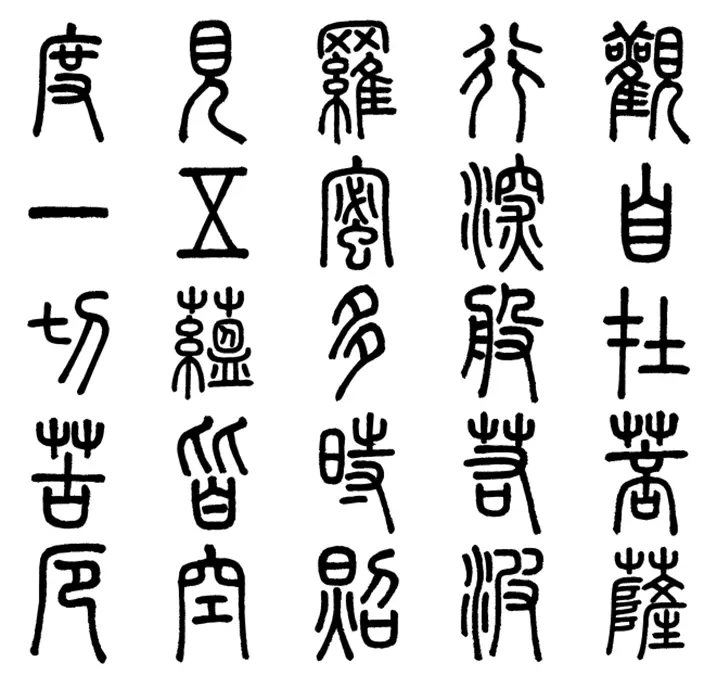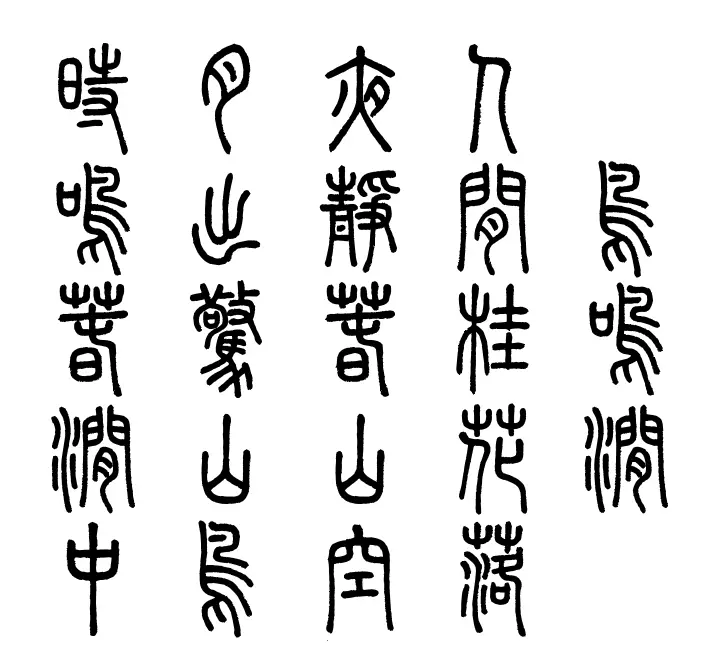
小篆是漢字的優秀字形,是人類文明的瑰寶,二千年來,深受廣大人民的喜愛。
小篆字形以《說文解字》為依據,《說文解字》雖然有一些板本的差異,但在文字學家的努力之下,絕大部分已取得一定的共識,問題不大。問題最大的是《說文解字》未收字,或《說文解字》之後產生的漢字。這些字沒有篆體,廣大的小篆喜愛者深感苦惱。歷代書法家也個別為一些字轉寫為篆體,但是沒有全面系統化的進行,也未能進入現代的電腦字體,所以當代的使用者無法享用到這些成果。也有電腦字體公司完成了全套的篆字字體,但是並未請教文字學家,所以成品難以過關,如「有」字寫成「」、「為」字寫成「」、「丟」字寫成「」等,都是讓人無法理解的形體。
王心怡女士學習小篆逾三十年,在臺師大、北師大學習文字學,又花了很大功夫編制《商周圖形文字編》,認認真真的把文字學專業學習通透。她有特殊的感受力,感受到上天要她完成篆字的書寫。而一向對電腦中文關心備至的謝清俊教授也提議要開發一套適合各界使用而又合於文字學專業要求的全篆字,在各種因緣具足的條件下,心怡欣然接受了這個任務。在謝教授的領導下,莊德明先生和我義無返顧的加入了這個行列。經過三年多的努力,這個工作基本完成了,令人欣慰。
崇羲篆體的製作體例,文字學方面的說明如下:
1、字數儘量求多,常用字、次常用字、罕用字、異體字,只要是典籍、文學、生活常用到的字,儘可能的收入。
2、見於《說文解字》的字,依大徐本《說文解字》的形體書寫。大徐本《說文解字》的板本差異,依據相關條件擇其善者從之。
3、大徐本《說文解字》同一個字,作為單字與作為偏旁時往往會有些微的差異,作為偏旁時也往往並不全同,如:「」、「」、「」、「」四字的「亢」就不相同,這其實反映了文字流傳中的實際情況,本字體完全依大徐本《說文解字》書寫,不予更動。而在書寫大徐本《說文解字》未收字時,則依單字字樣書寫,如:「」、「」。
4、不見於大徐本《說文解字》的字,依據合理的字形結構,採用《說文解字》的小篆偏旁轉寫。如「床」字,《說文解字》作「」,從木爿聲。但是坊間都寫成「床」,標準字體也規定作「床」,《幹祿字書》已經指出這是個俗字,崇羲篆體也只能依據俗字從廣從木寫成「」。
5、有些後起字的結構難以考訂,或眾說不同,只能擇善而從,無法求備,如「丟」字,《字彙》釋為「一去不還也」,或以為從「去」,「撇」為指事符號。二說皆有理,姑從《字彙》舊說作「」。
7、目前可見的篆體很多,各有各的製作目的。崇羲篆體主要是為了針對一般使用者設計,擺脫學術的槓槓,不以單一板本為限,也不以此為標準篆體。希望各界察諒。